С помощью Homeless Fonts почерк бездомных становится дизайнерским шрифтом
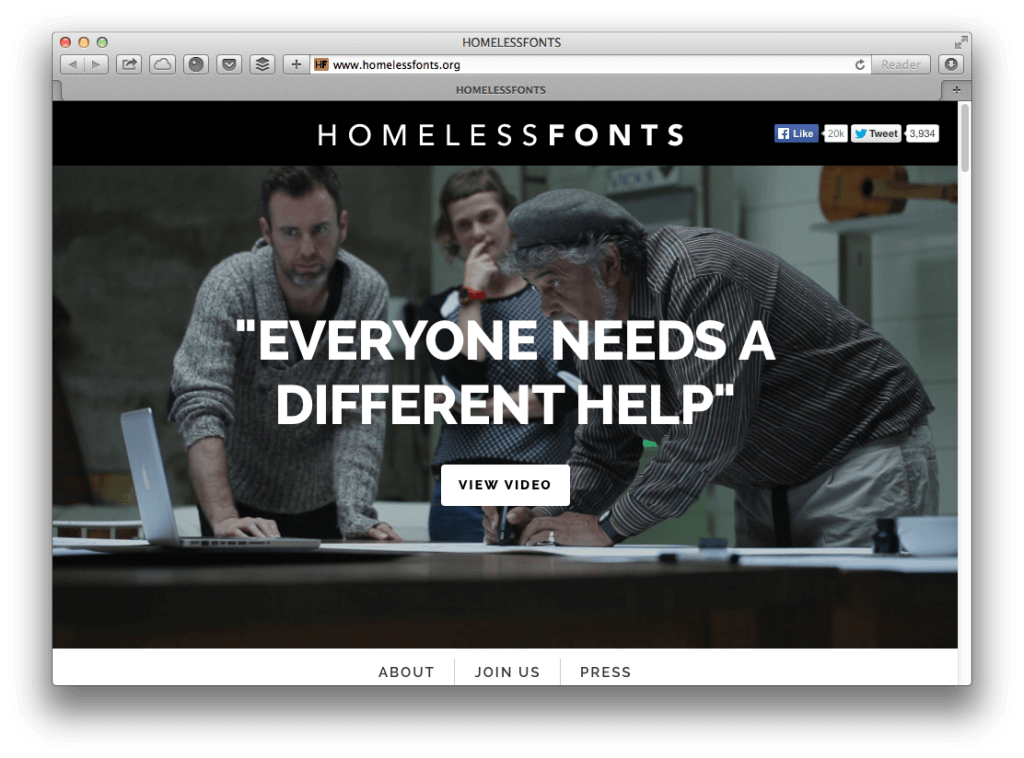
Homeless Fonts — проект из Испании, который берет почерки с табличек бездомных людей и делает на их основе дизайнерские шрифты.
Часть прибыли идет авторам для того, чтобы они смогли изменить свою жизнь к лучшему. Проект стал результатом совместной работы рекламного агентства The Cyranos McCann и фонда Arrels.